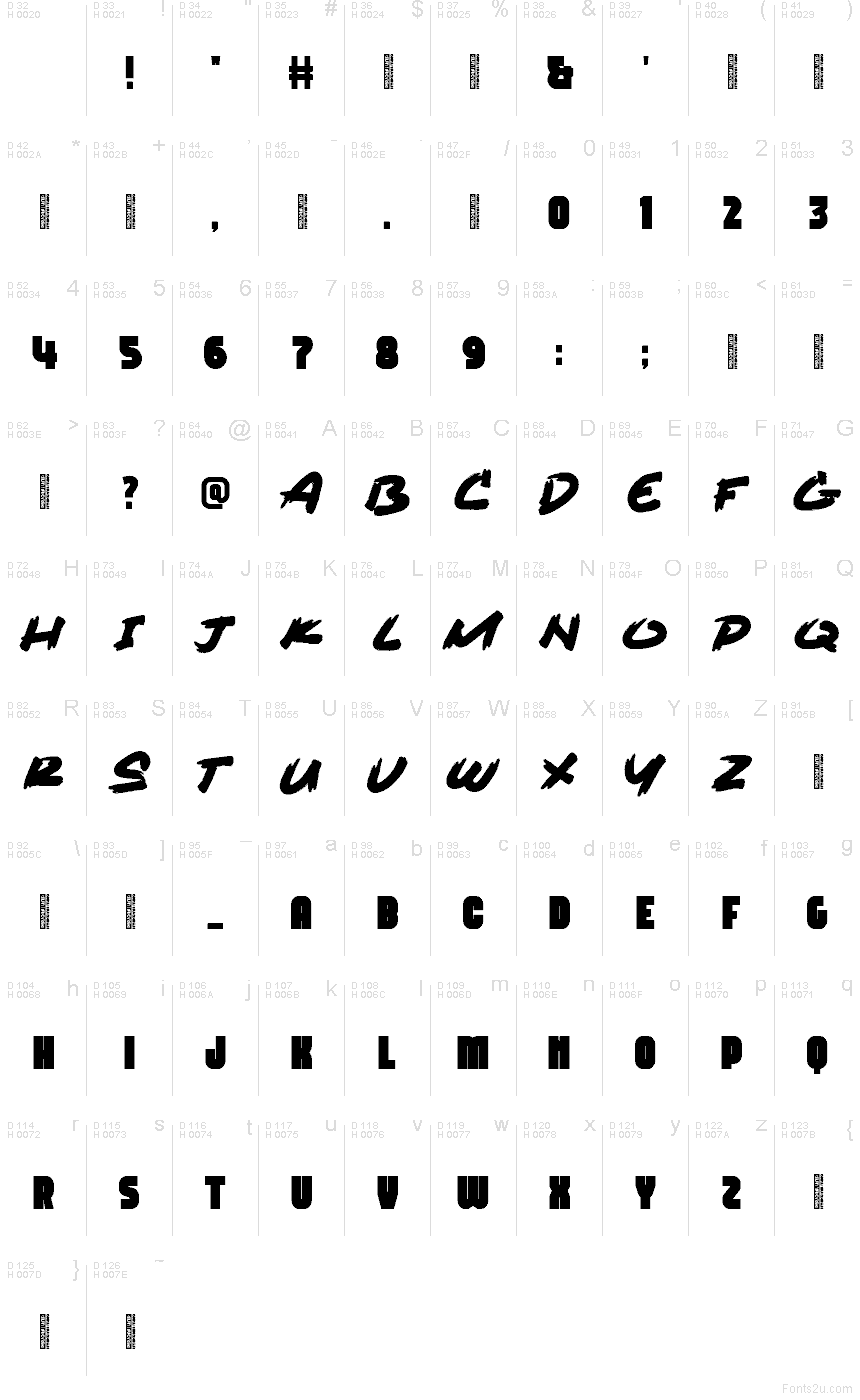
Silverthorne, di Lettercorner Studio, è un font display gratuito in stile pennello, carico di un'energia grezza e artigianale. Le lettere sembrano trascinate con un pennello carico d'inchiostro: forme larghe e massicce, spezzate da bordi irregolari, striature asciutte e punte affilate, che donano alle maiuscole un carattere da poster urbano piuttosto che la pulizia di una classica scrittura a mano.
È perfetto ovunque serva quel pugno visivo: flyer musicali, branding streetwear, poster per eventi, packaging e titoli d'impatto sui social media. Come font gratuito, Silverthorne si distingue soprattutto in titoli brevi, copertine e scritte grafiche, dove i tratti robusti e le texture graffianti rendono attiva e dinamica anche una singola parola.